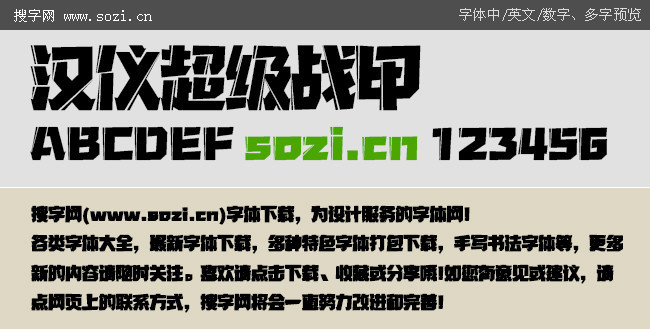
漢儀超級戰(zhàn)甲
搜字網(wǎng)給大家提供一款漢儀超級戰(zhàn)甲中文字體下載,是一款由漢儀字庫全新推出的藝術(shù)字體。該字體充滿了科技感、機械感、力量感,具有強烈的視覺沖擊力,適合應(yīng)用于書籍設(shè)計、平面海報設(shè)計、包裝設(shè)計等廣告應(yīng)用。(本字體為個人非商用版,如需要商用請聯(lián)系漢儀公司購買版權(quán))